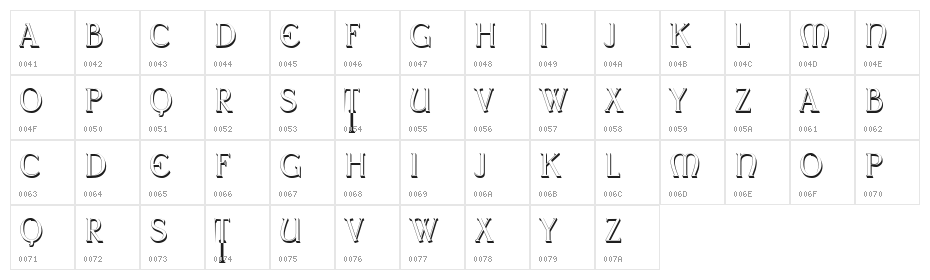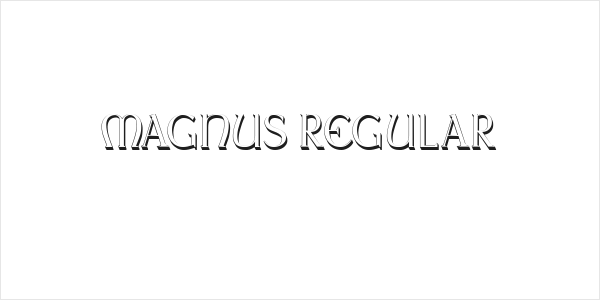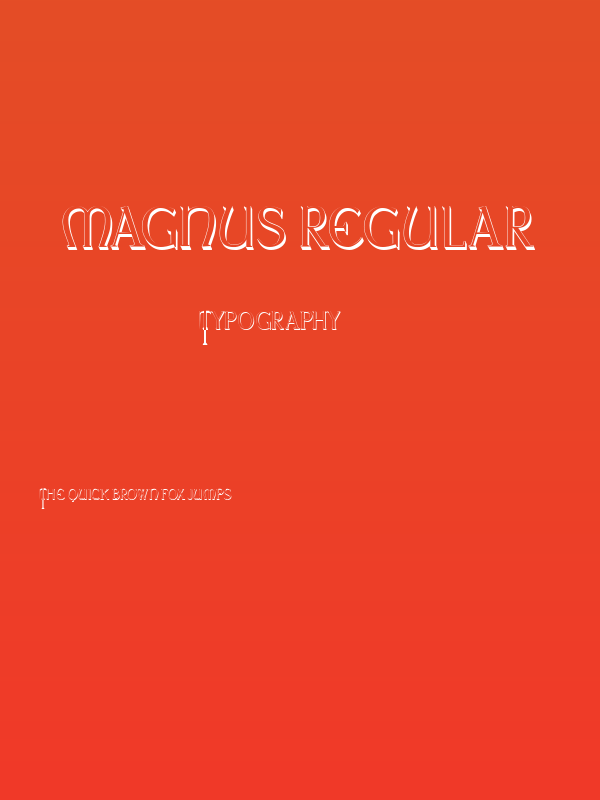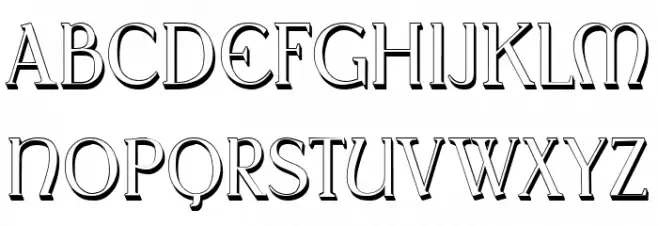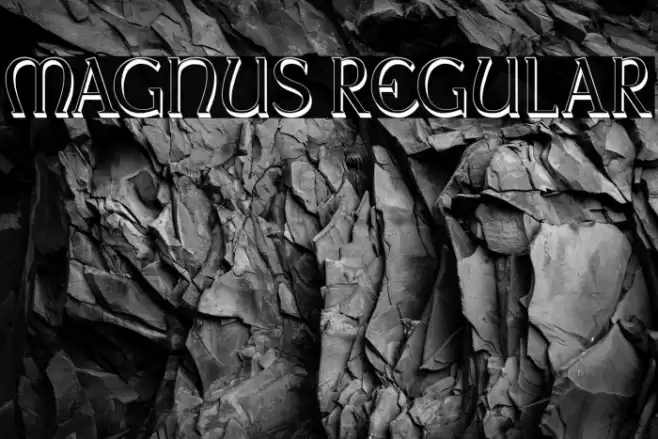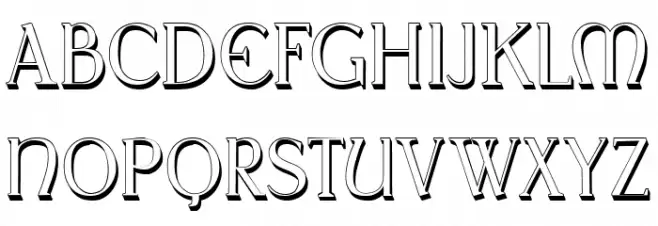
Magnus Regular Font
| Proiecte propuse | This font is perfect for projects that require a strong visual impact, such as posters, banners, and branding materials. Its bold style makes it suitable for logos and titles that need to stand out. |